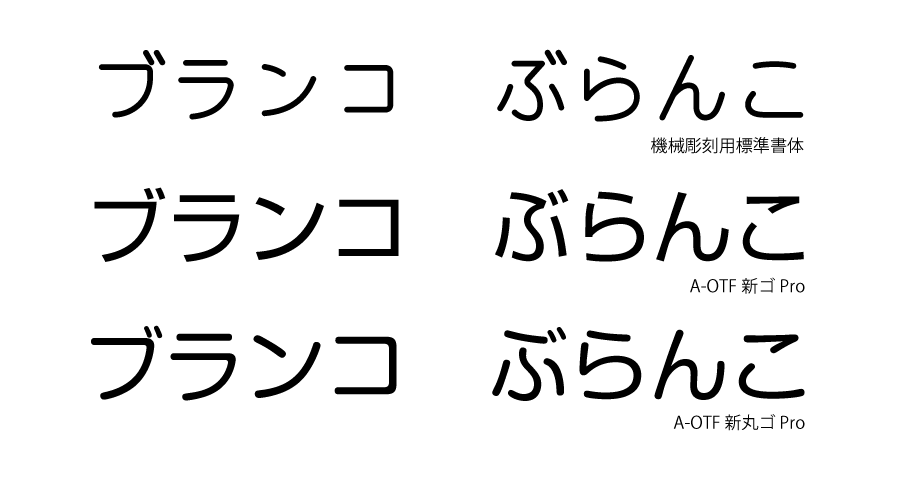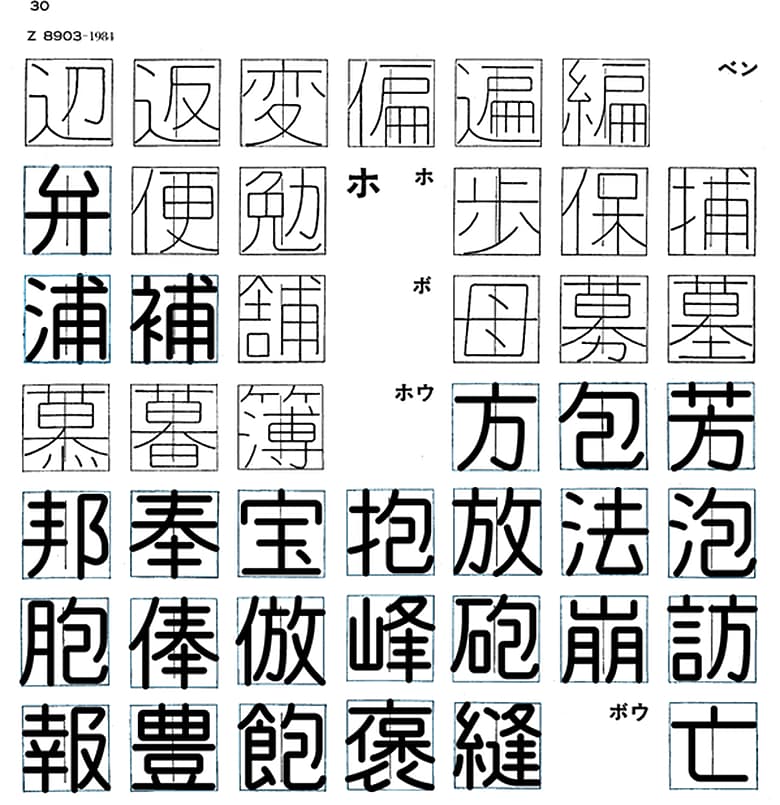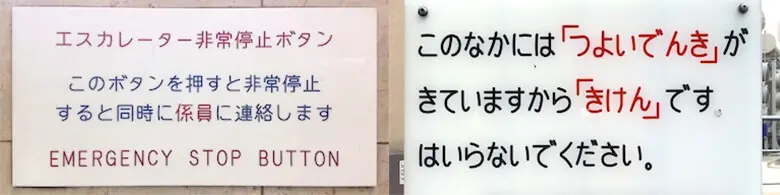
街でよく見るあの書体がデジタルフォント化!機械彫刻用標準書体フォント
歩道橋のプレートや、レトロなマンションでの注意書きなど、さまざまな場所で使われている、こんな書体を見たことがありますでしょうか。
これは「機械彫刻用標準書体」と呼ばれ、日本工業規格(JIS)によって、工業的な彫刻で文字を作成する際の標準となる書体として定められているものです。
特徴のある書体
機械彫刻標準書体は、機械の刃が回転しながら軌跡を描くように彫刻していくため、縦も横も同じ線幅で、線の終わりは半円形になるという特徴があります。
線が1か所に集中するのを避け、交わる部分の角度は直角、角は曲線に、ハネや筆押さえをはぶき、なるべく線が連続するように…など、文字を彫る原版をなるべく傷つけないよう、また彫刻する際の作業効率をあげるために、様々なことが決められています。
工業彫刻の持つさまざまな制約に配慮してつくられた、機能美の書体なのです。
他のゴシック体の書体と比べてみると違いが明らかですが、"ふところ”がとても広くとられていて、柔らかい印象で読みやすいのも特徴のひとつです。
この味わい深い書体を自主制作でデジタルフォントにしてくれたのは、Kirnuraさん。
現段階で、ひらがな134グリフ(※グリフは書体を数える単位)、カタカナ134グリフ、漢字548グリフ…と、収録されている字の種類はまだまだ限られていますが、今後も収録字種はどんどん増えていくそうです。
この機械彫刻標準書体もKirnuraさんがデジタルフォント化してくれたことによって、DINのように広まるかもしれませんね。